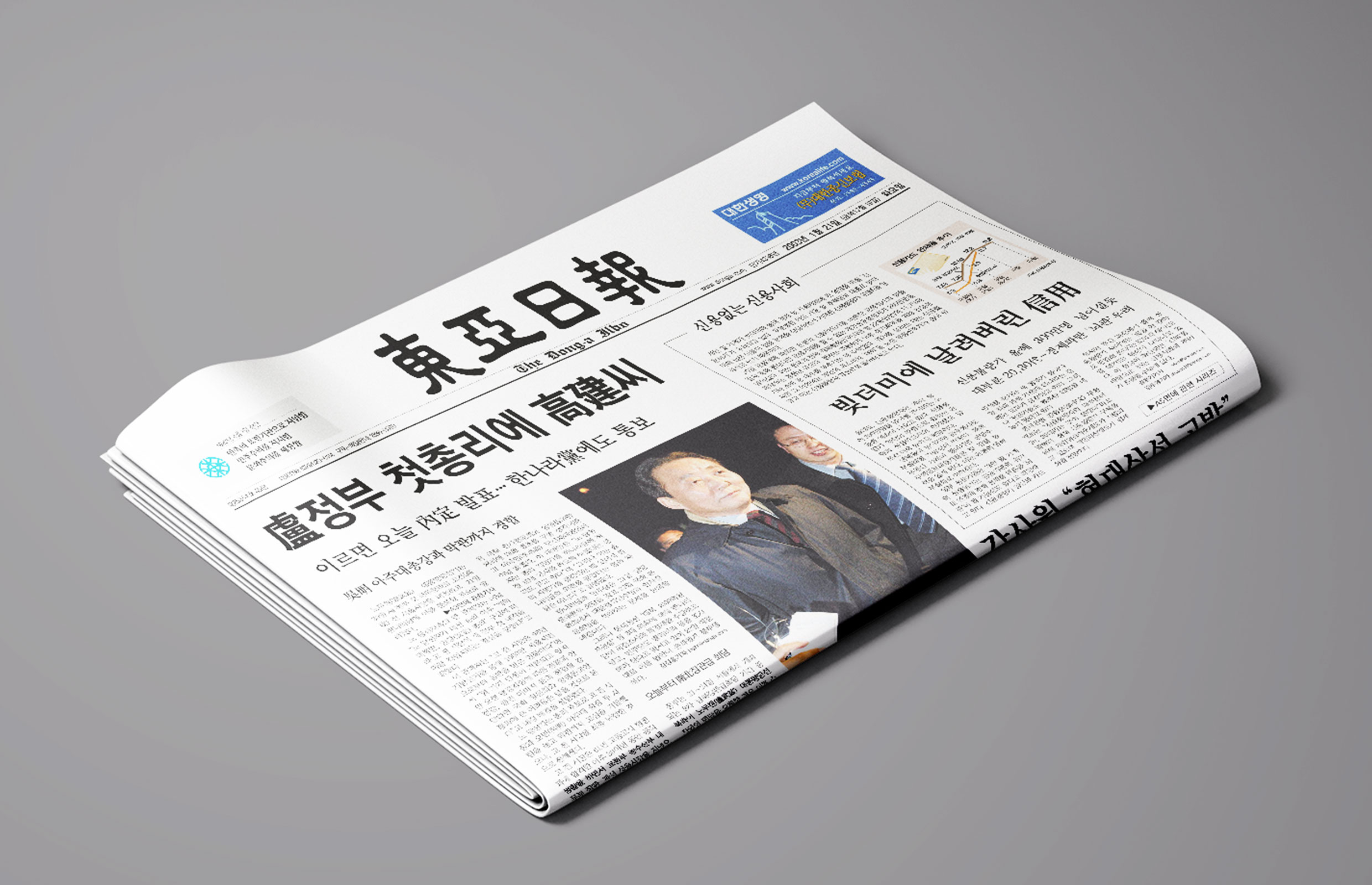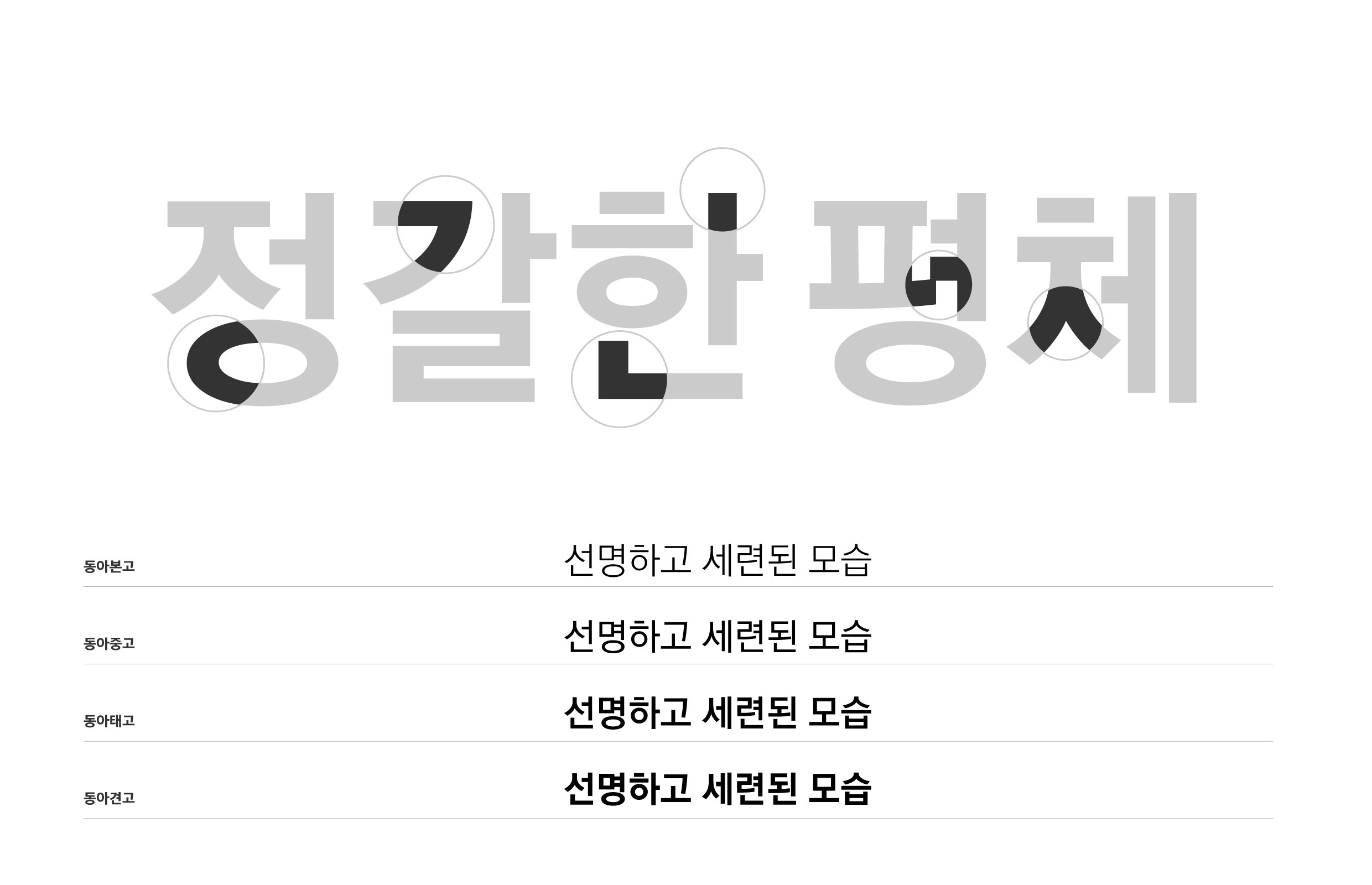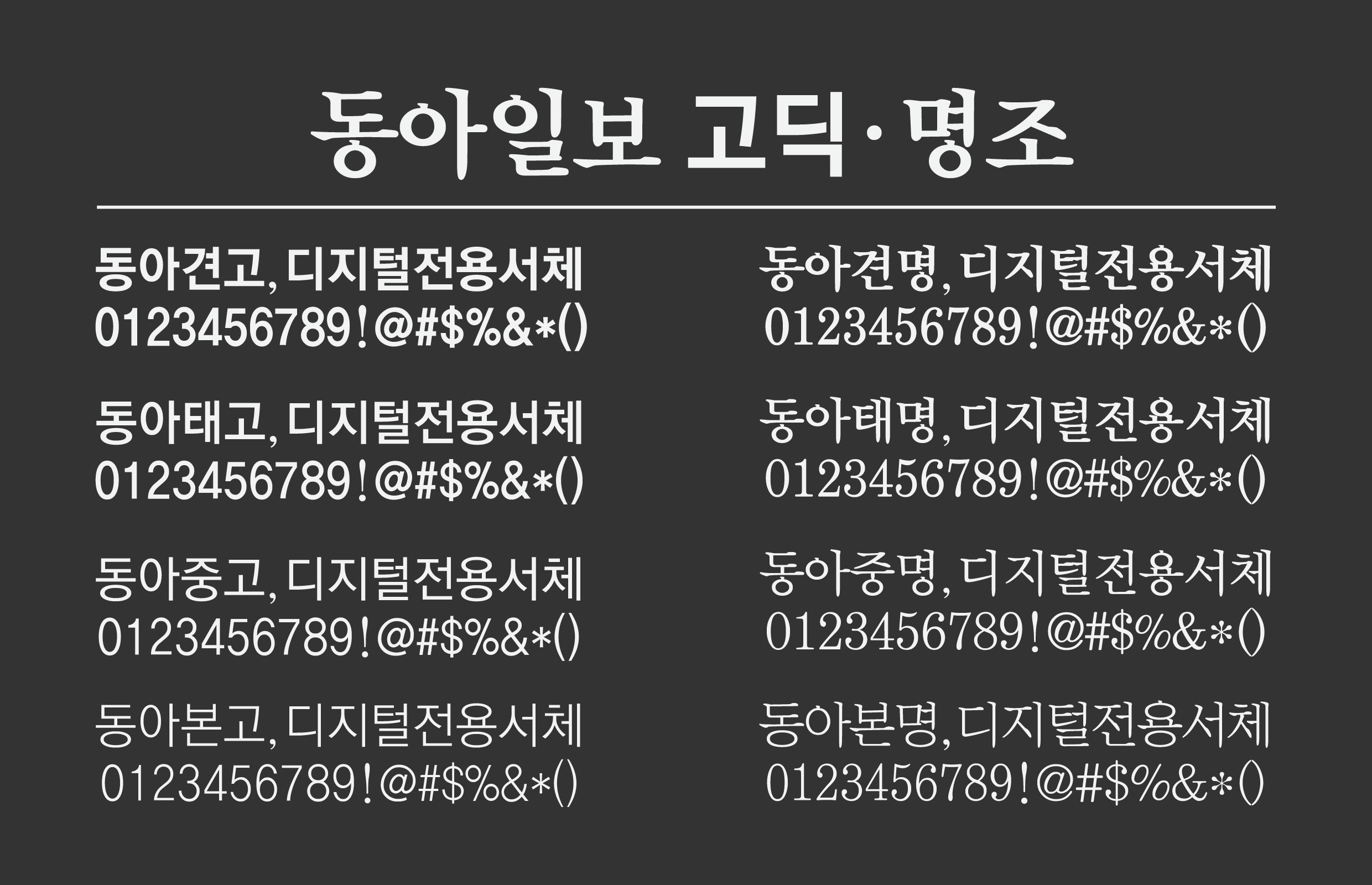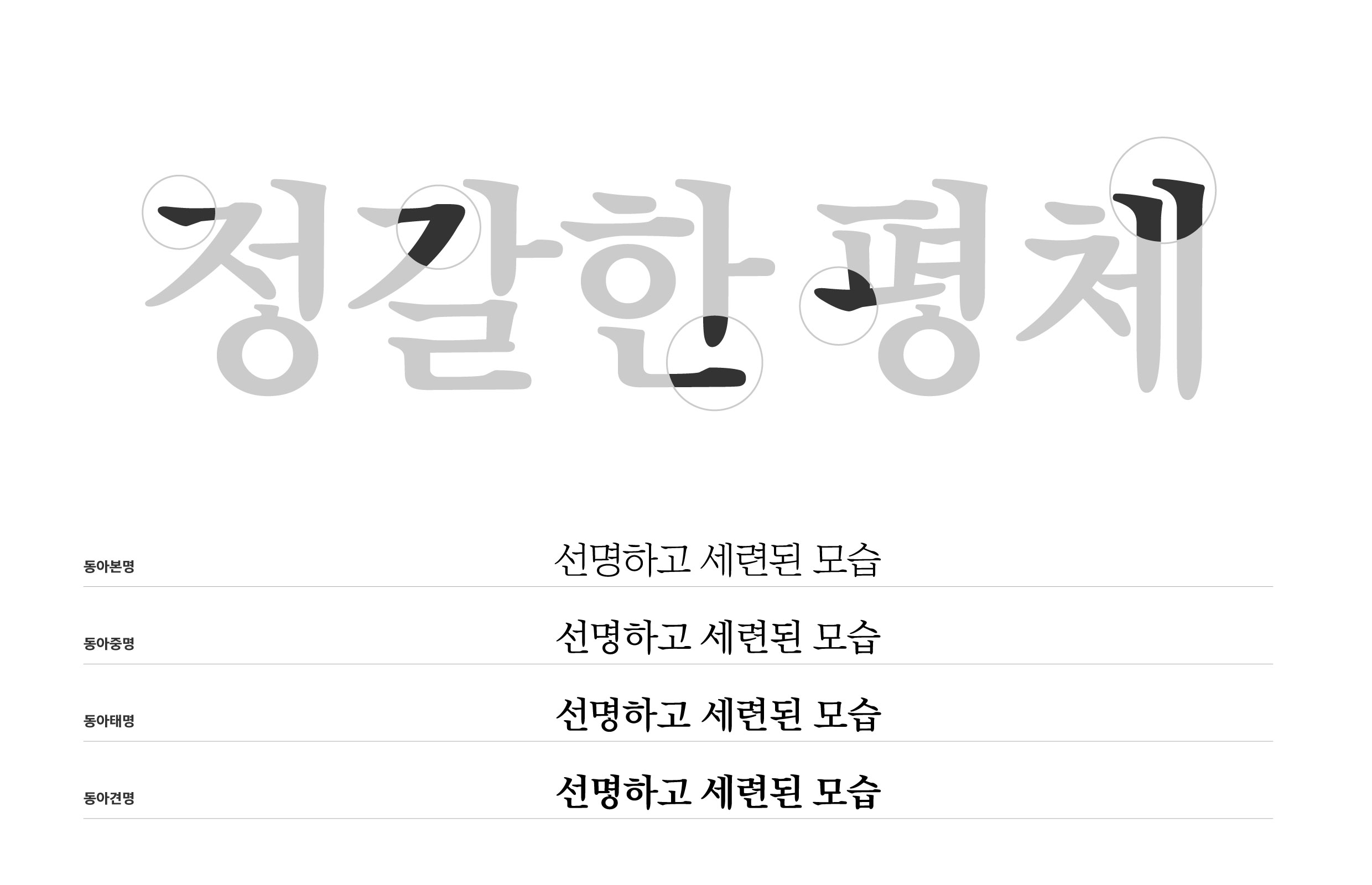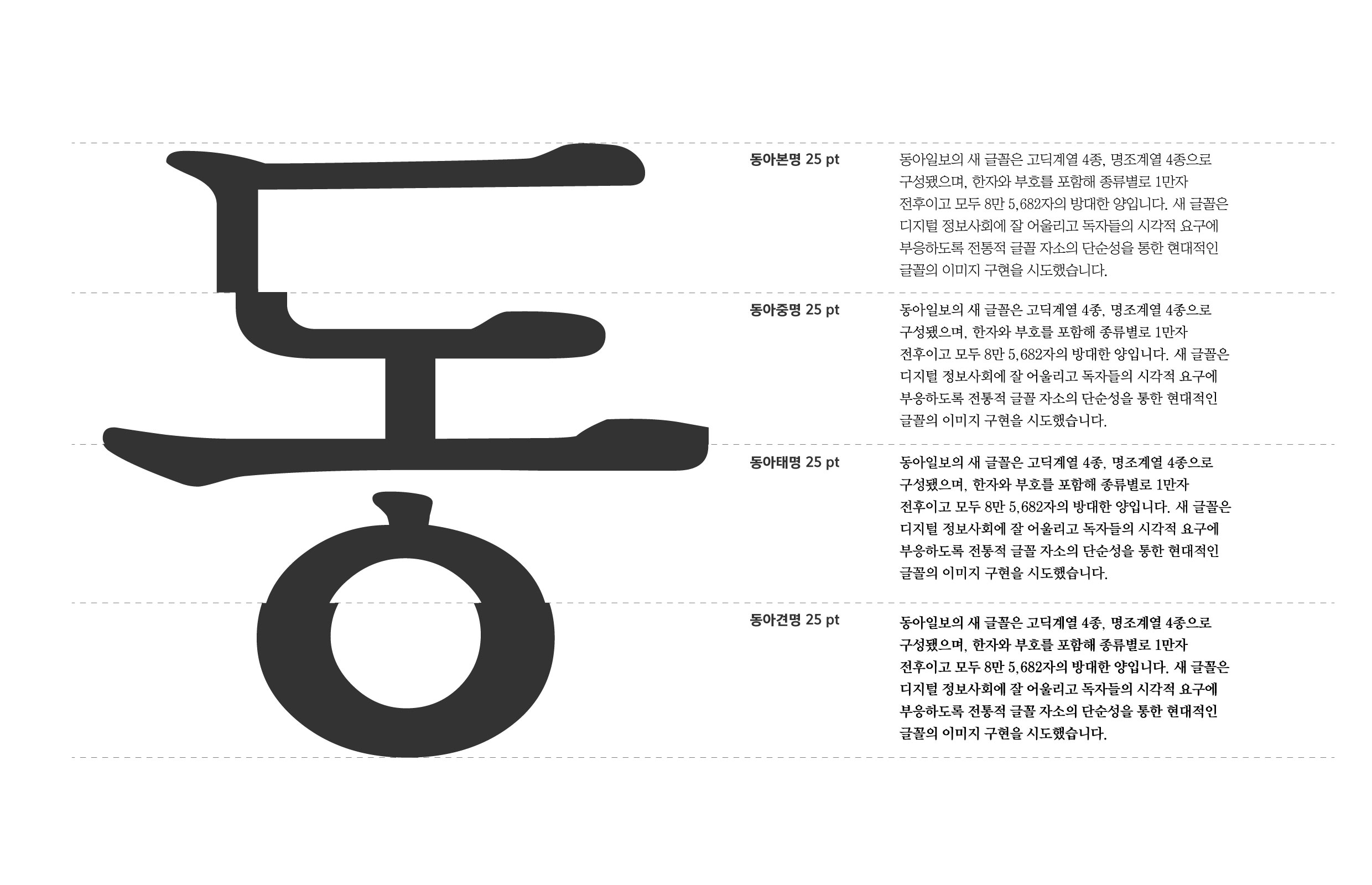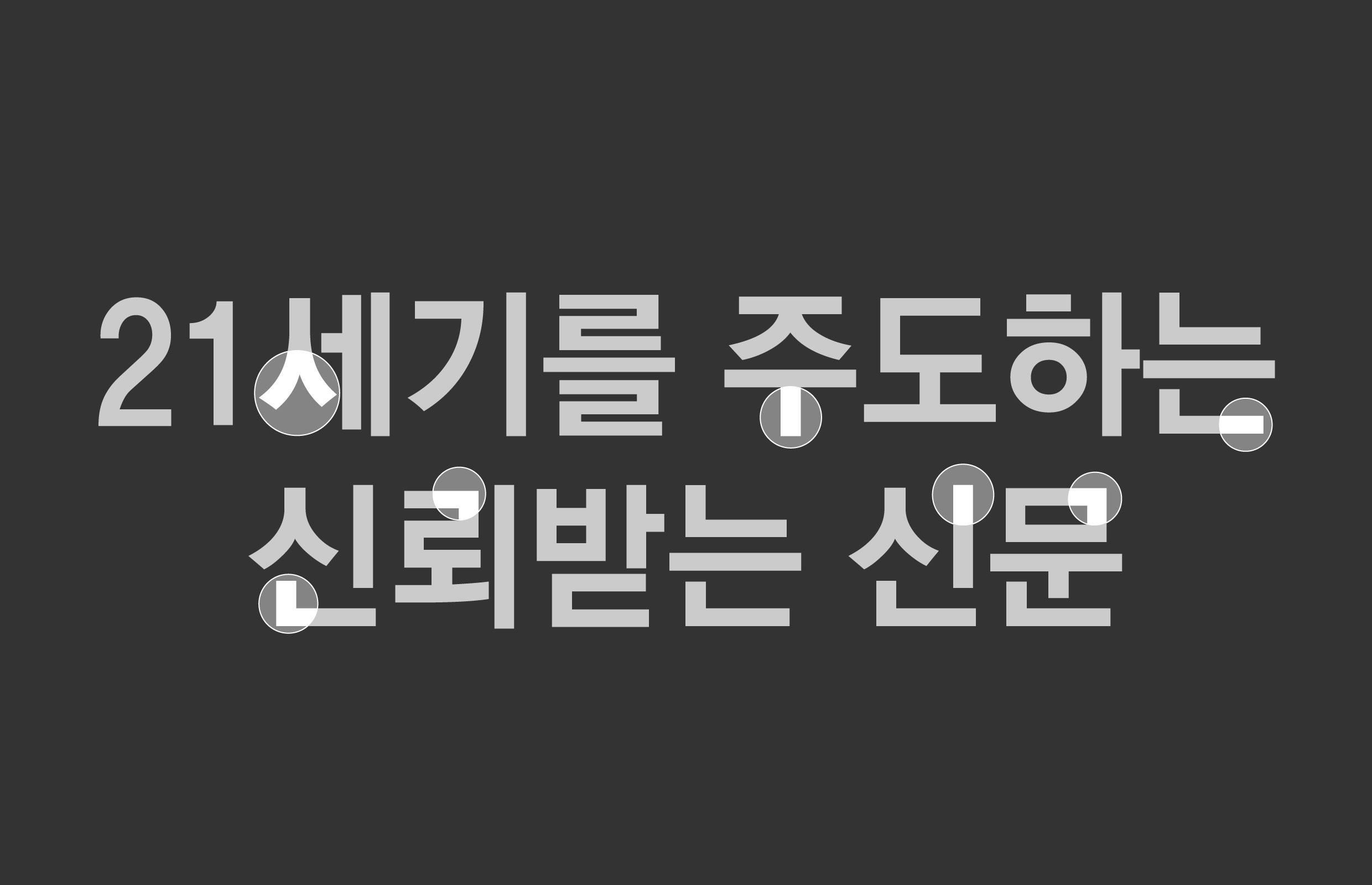
동아일보사 [동아일보]
동아일보사 [동아일보 고딕, 명조]
1988년 전면 가로쓰기 전환 이후 줄곧 사용해 온 본문 및 제목 글꼴을 과감히 버리고 새로운 전용글꼴을 개발하려 한 동아일보의 강한 의지가 담긴 프로젝트. 동아일보가 가진 저력과 디지털 정보 사회에서의 비전을 바탕으로 독자와 보다 명료하게 의사소통 할 수 있는 글꼴을 개발했다.
동아일보